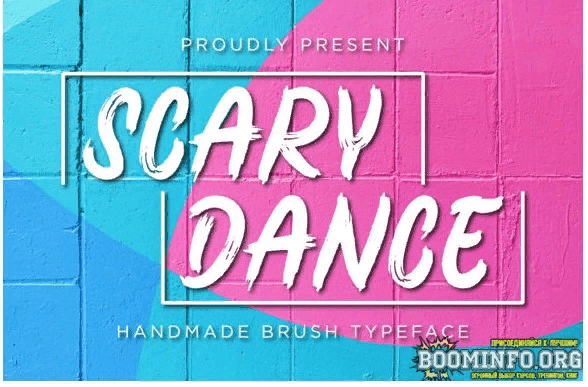
Название: Scary Dance Font
Scary Dance - это крутой и смелый матовый шрифт.
Он воплощает игривость и подлинность и идеально подходит для любого детского мероприятия или школьного проекта.
Название: Scary Dance Font
Scary Dance - это крутой и смелый матовый шрифт.
Он воплощает игривость и подлинность и идеально подходит для любого детского мероприятия или школьного проекта.